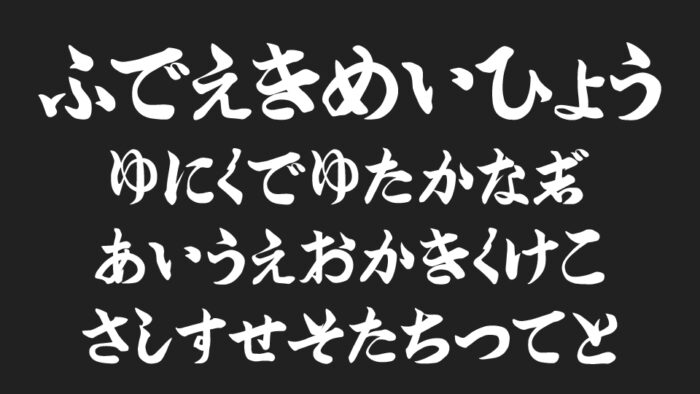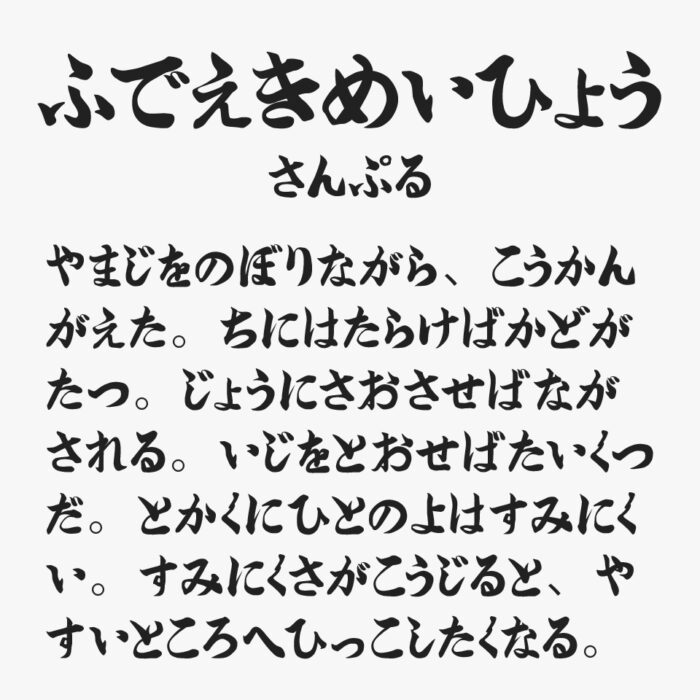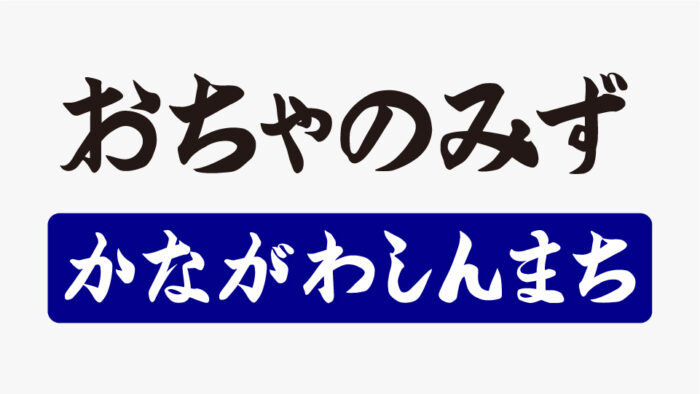
筆文字駅名標フォント
筆文字駅名標フォントは、昔の駅名標や各種看板の筆で書かれた文字を再現した筆文字フォントです。
明治・大正・昭和戦前期の駅名標(駅の看板)には、筆文字風の書体が多く使われていました。漢字は毛筆風の楷書体や行書体が多く、職人が筆で書いたような文字でした。
昭和中期以降は、印刷技術の普及により、少しづつ活字風・ゴシック体が主流へ移行されていきました。
筆文字駅名標フォント、それまで活躍していた筆文字駅名標を再現してユニークなフォントとなっています。
収録文字は、ひらがなが収録されています。
カタカナ×
漢字×